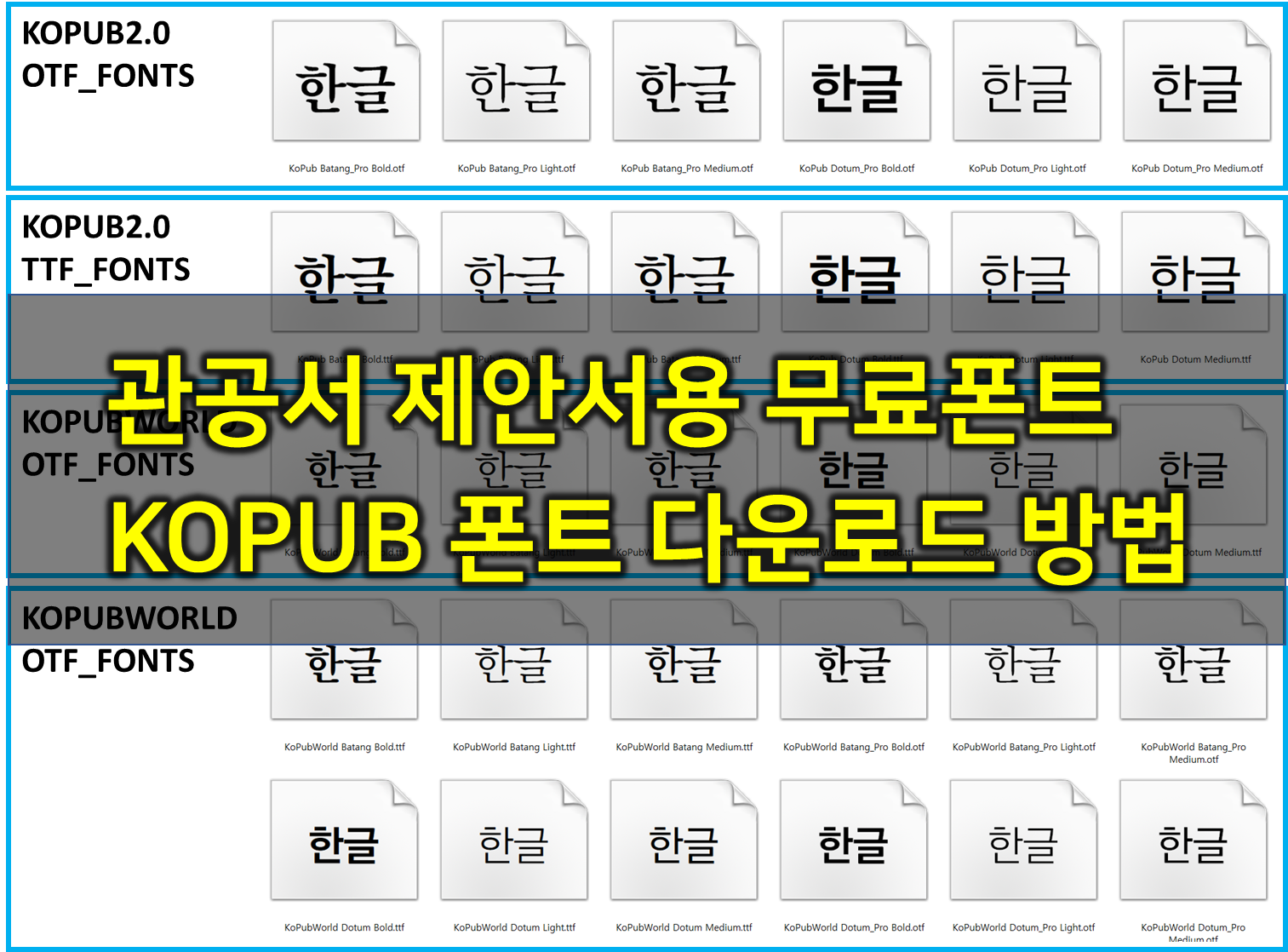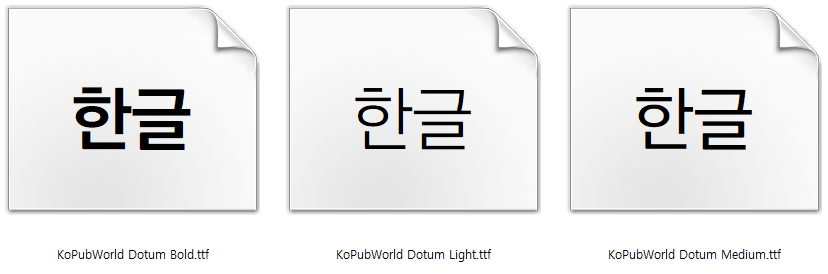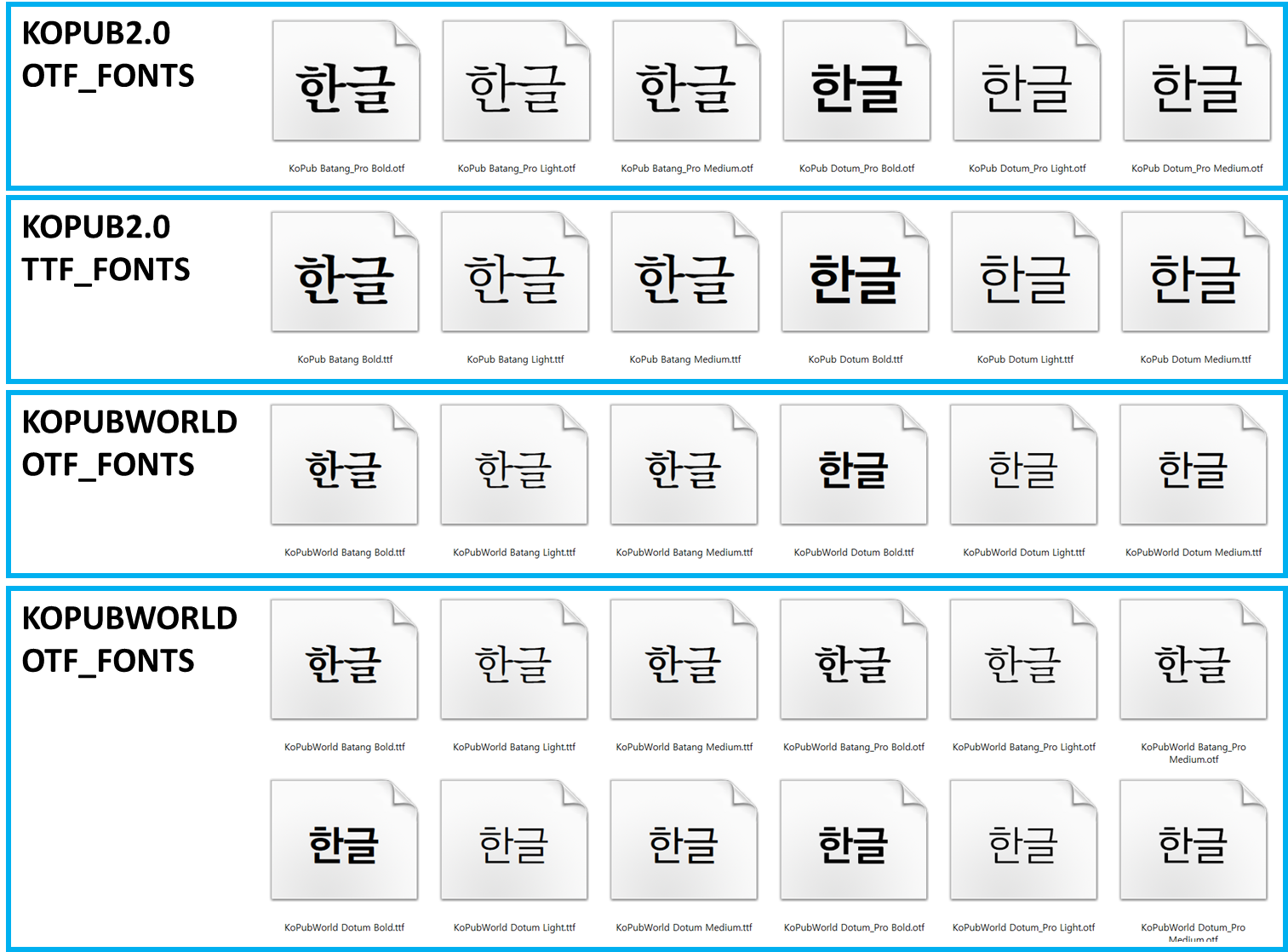
문서 작업을 할 때 글꼴(폰트)은 매우 중요합니다.
제가 백화점 기획 업무를 담당했을 때 하루종일 엑셀과 PPT로 업무를 했는데요.
특히 PPT 작업에서 굵은 글씨를 표현할 때 나눔고딕 EXTRA BOLD 같은 폰트를 써 주고, 보충 설명을 고딕체로 해줘야 강조와 설명이 조화를 이루게 됩니다. 똑같은 폰트로 글씨 크기와 굵기만 다르게 표현하는 것보다 훨씬 시인성 및 문서 디자인 측면에서 좋은데요.
IT 업계로 전향하고 나서도 고객사(주로 국내 최상위 대기업)에서 사용하는 문서 수준에 맞게 작업을 해야 하기 때문에 여전히 MS오피스 업무를 많이 하고 있습니다.
오늘 업무상 필요로 인해 과거 저희 회사에서 작성했던 제안서를 검토하던 중 처음 보는 글꼴이 있어 확인해 봤습니다.
해당 글꼴이 제 PC에 설치돼 있지 않기 때문에, 문서 상의 글꼴들이 깨진 상태로 보이게 되는데요.
이럴때 당황하지 마시고, 문서 상단에 있는 '글꼴'을 클릭하여 어떤 폰트인지 확인한 후 포털 사이트에서 검색하시면 됩니다.
해당 글꼴이 설치되어 있지 않더라도 폰트창에 어떤 글꼴인지 이름이 나오는데요. 이걸 찾아 설치하시면 됩니다.
위 폰트는 '한국출판인회의'라는 곳에서 배포하는 무료 폰트 'KoPub돋움체 Pro'로 확인되었습니다.
무료 폰트라도 상업적 이용 금지 등 여러 제약 사항이 걸려있는 경우가 많은데요.
전자책에 사용되는 폰트이군요. 그래서 시인성이 좋은 폰트일 것 같다는 생각이 듭니다.
KOPUB 폰트 4가지 비교
개인적으로 문서 작성용으로는 KOPUB의 4가지 폰트 중, 'KOPUBWORLD OTF 폰트가 고딕체로서 가장 좋아 보입니다.
특정 회사에 제안서를 제출할 때 그 회사에서 사용하는 폰트가 어떤 것인지 사전에 여쭙고 작성한다면 그 제안서에 한 번이라도 더 관심이 갈 것 같습니다. 제가 백화점에서 수많은 제안서를 검토했을 때 오타가 있거나 양식이 서툴면 해당 제안 자체를 좋지 않게 봤던 경험이 있습니다. '잘 작성된 제안서 = 업무력' 입니다.